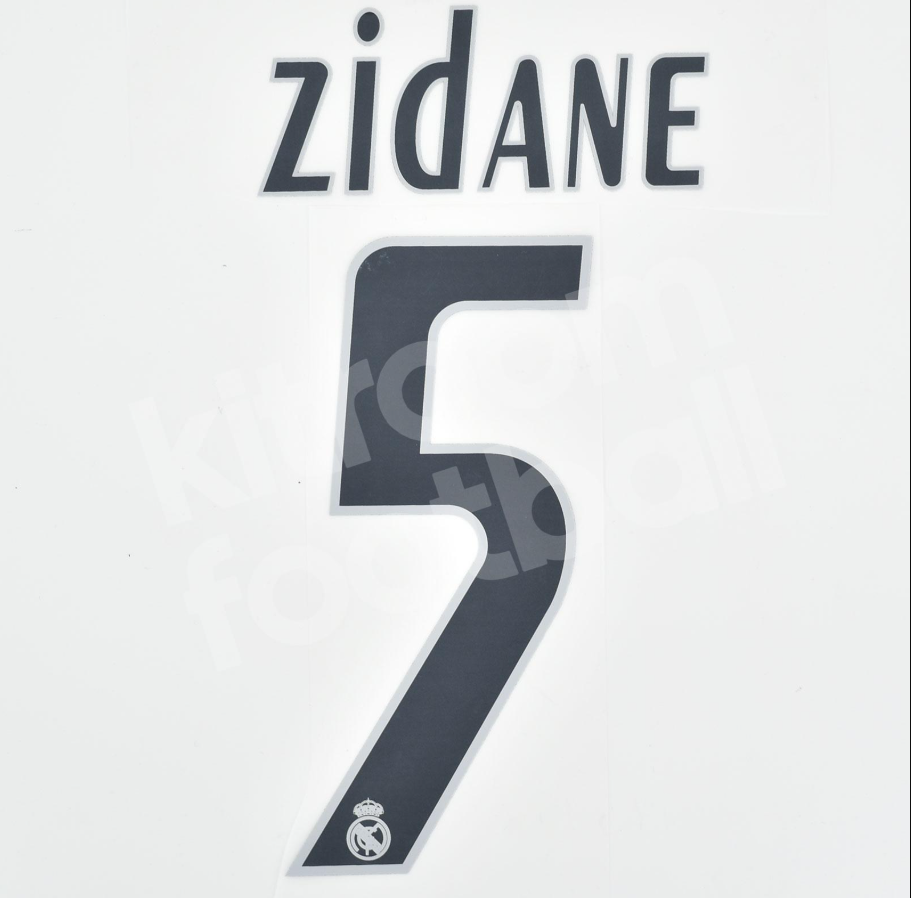
Volte ao auge do estrelato do futebol mundial. A temporada 2005-2006 do Real Madrid não foi apenas mais um ano na história; foi o palco onde lendas como Zidane, Ronaldo Fenômeno, David Beckham, Roberto Carlos e Raúl desfilaram juntos.
Para recriar a magia daquele time, trazemos para você a tipografia oficial utilizada pela Adidas nos uniformes daquela época. Se você deseja restaurar uma camisa antiga, criar um mockup nostálgico ou estampar uma réplica com precisão histórica, este arquivo é indispensável.
Estilo Visual e Identidade
A fonte desenvolvida para o Real Madrid em meados dos anos 2000 reflete a transição da Adidas para designs mais dinâmicos e futuristas.
Com traços arredondados e uma estrutura “gordinha” (bold), essa tipografia se destacava pelo alto contraste nas costas do uniforme branco imaculado. Um detalhe crucial dessa época era a aplicação dos nomes em arco (curvados) acima do número, uma característica marcante que você pode replicar no seu software de edição para dar aquele toque final de autenticidade digno de um uniforme de Champions League.